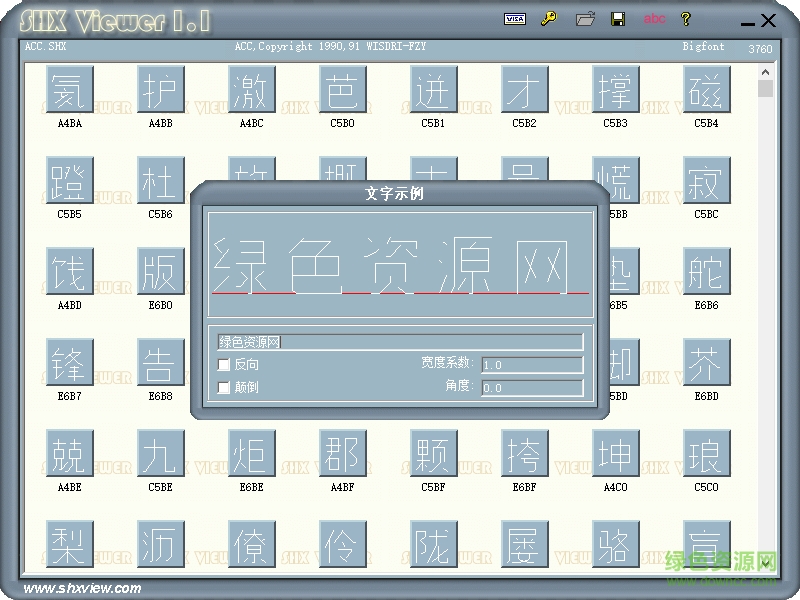
ACC.SHX字體用于autocad軟件。這款cad字體非常優(yōu)雅簡潔,綠色資源網(wǎng)小編推薦給各位工作中需要使用cad的小伙伴。歡迎下載!
ACC.SHX是專為AUTOCAD軟件打造的一款字體文件,一般在設(shè)計(jì)圖紙的時(shí)候使用,電腦中缺少了acc.shx字體,將無法正常查看CAD圖紙。